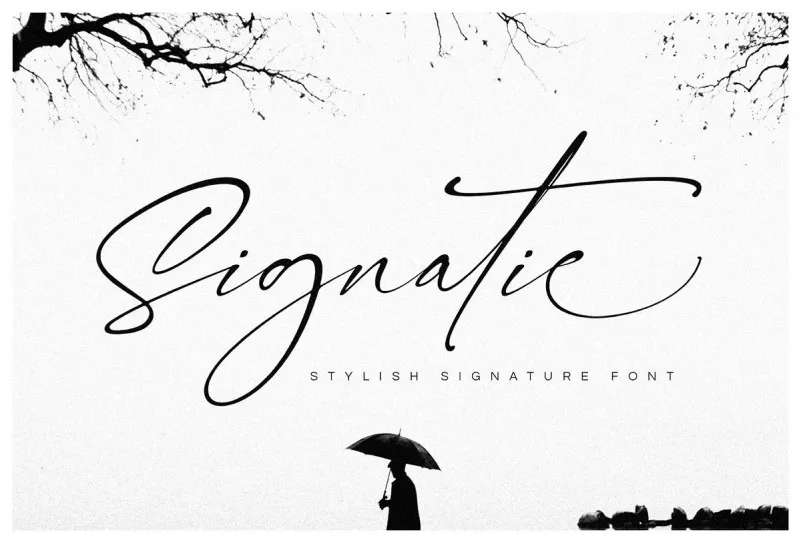
Signatie Signature Font – Download Grátis
Introduzimos a Signatie Signature Font, uma elegante tipografia escrita à mão. Perfeita para qualquer design que exija um toque refinado e moderno, seja para logos, convites de casamento ou aniversário, cartas de boas-vindas ou até mesmo materiais de marca. A Signatie foi criada pelo Designer 178-MC e é uma fonte aberta com recursos OpenType que inclui ligaturas e final swashes. Não se esqueça de usar números, pontuação e suporta outras línguas para tornar o seu design ainda mais autêntico. Este tipo de fonte é ideal para quem busca um toque refinado e elegante em seus projetos, seja para cartões de boas-vindas ou materiais de marca. Signatie é uma excelente escolha para adicionar um toque atraente e moderno aos seus trabalhos gráficos. Seja na hora de criar cartazes, posteres ou até mesmo cartões de visita, o resultado será sempre profissional e de alta qualidade. Com Signatie Signature Font, você tem toda a elegância que precisa em seu projeto, mas com uma personalidade única e moderna que se adequa perfeitamente aos mais diversos usos.